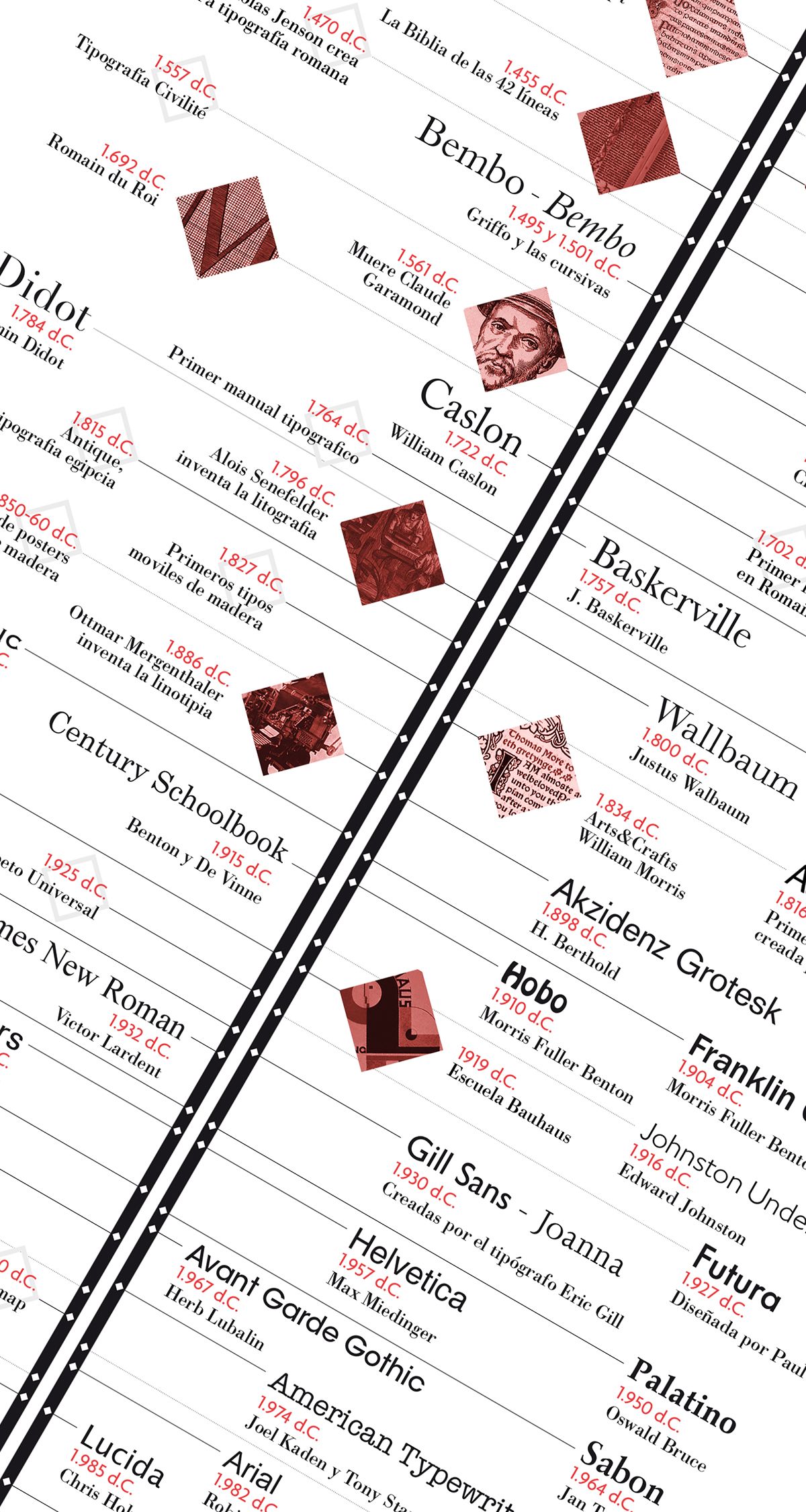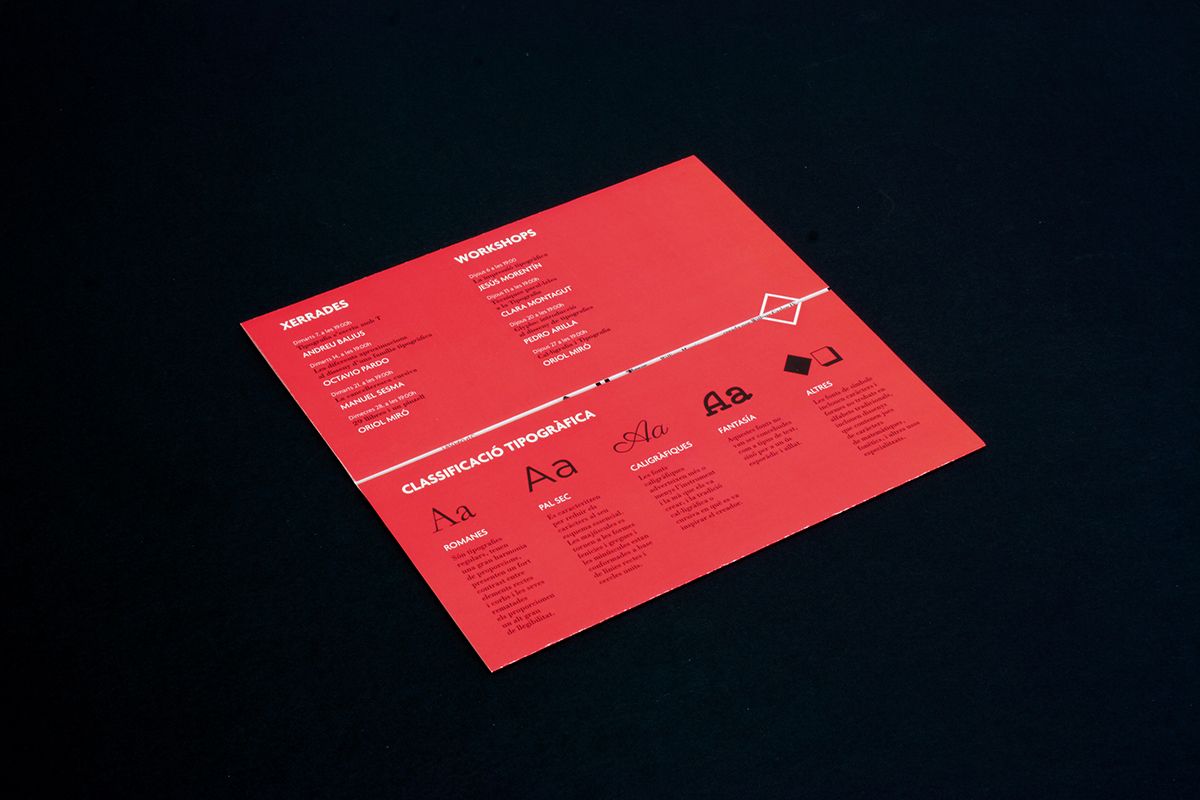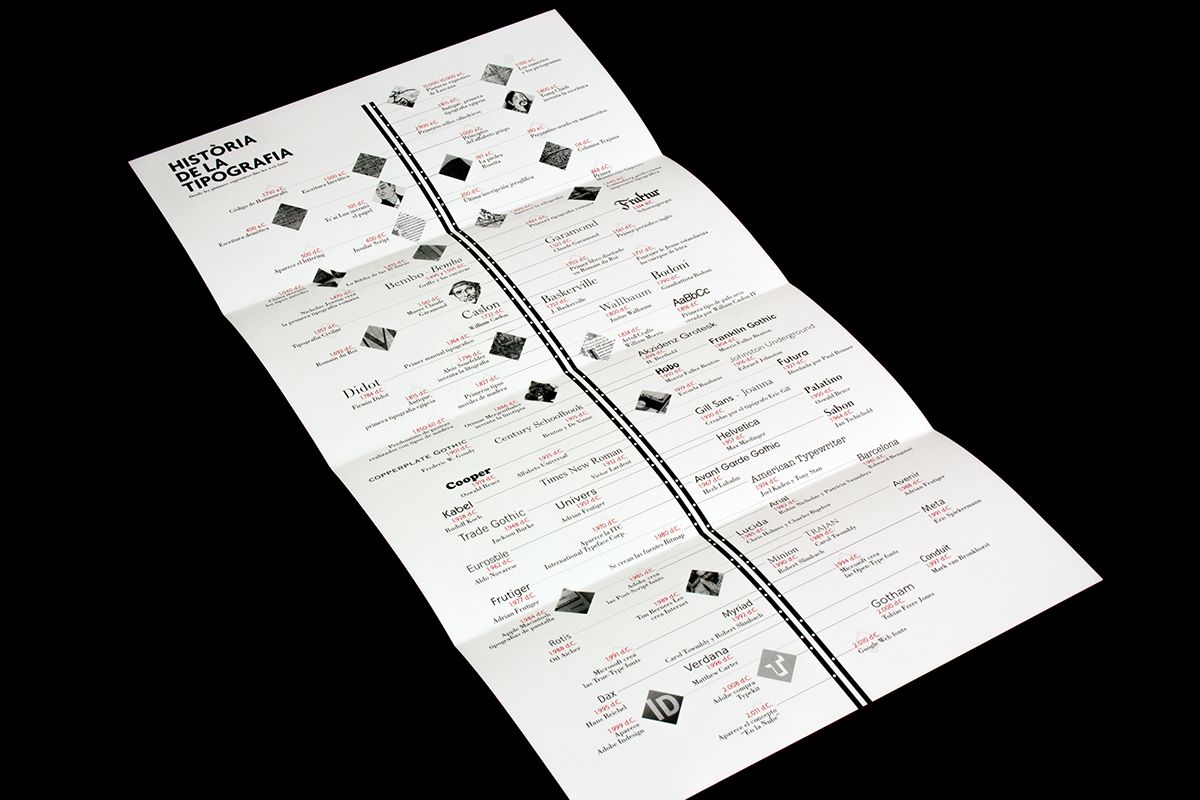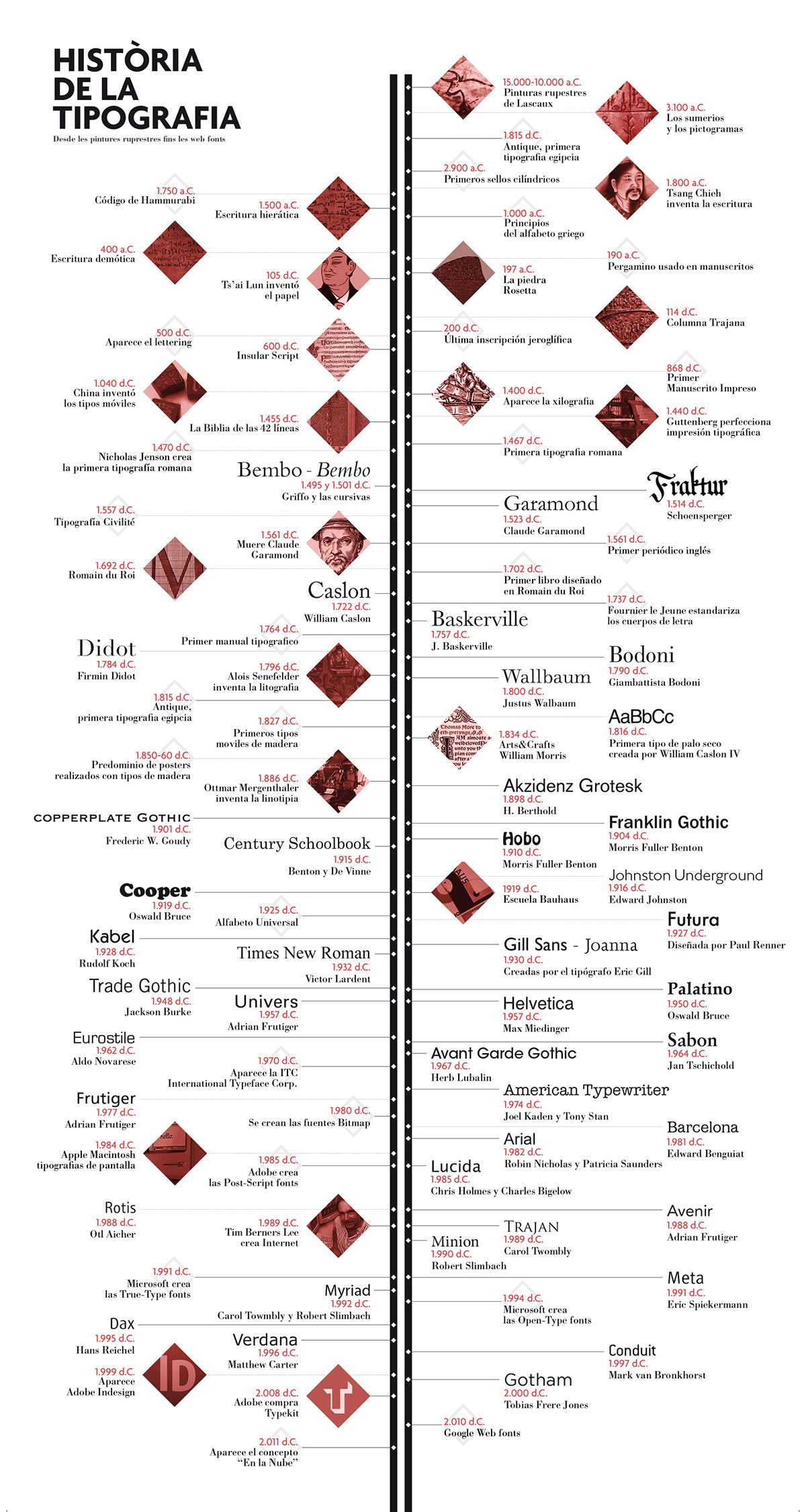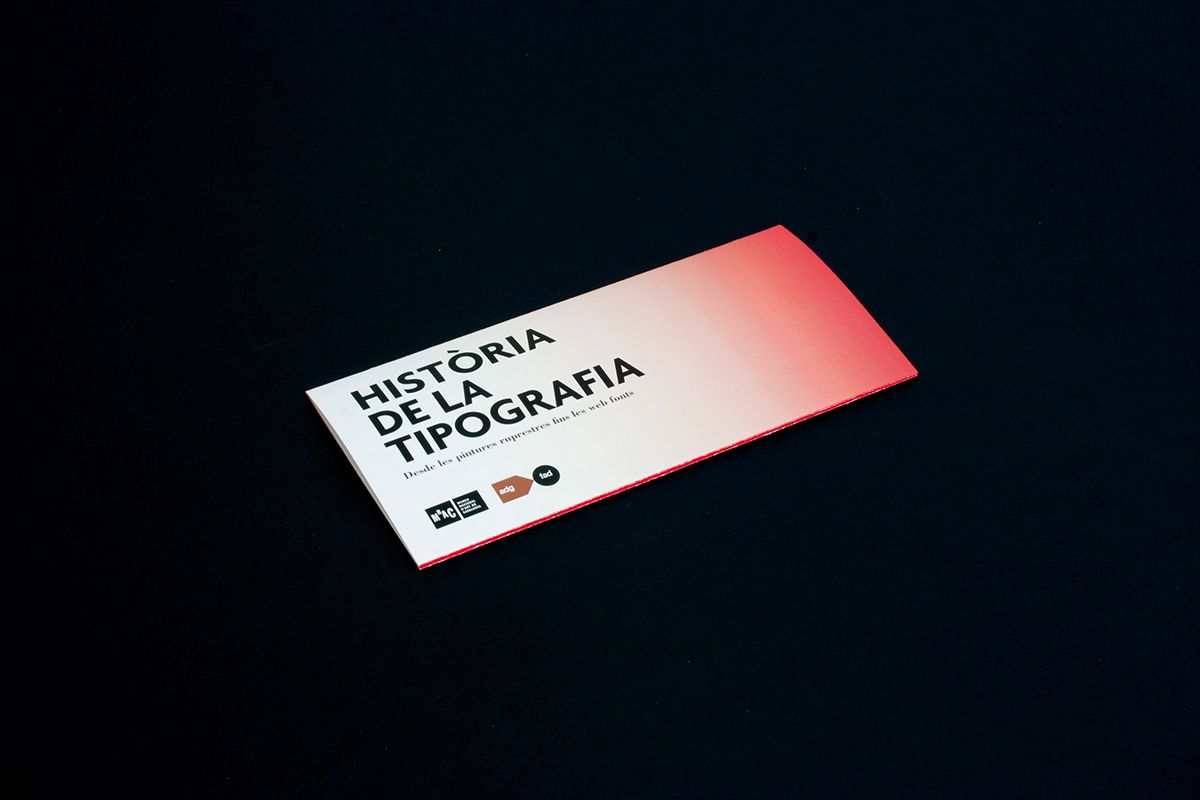
Historia de la Tipografía
Tipografia
Historia de la tipografia, desde las pinturas rupestres hasta las web fonts.
History of typography, from cave paintings to the web fonts.